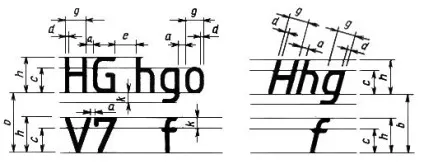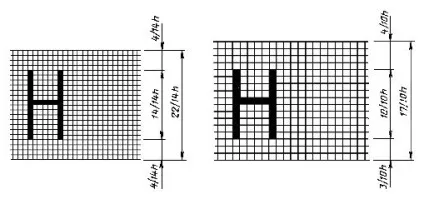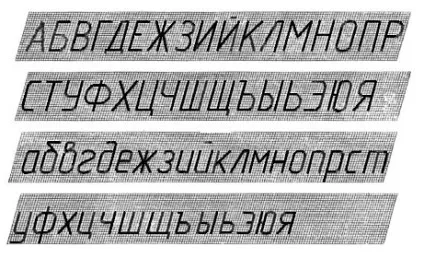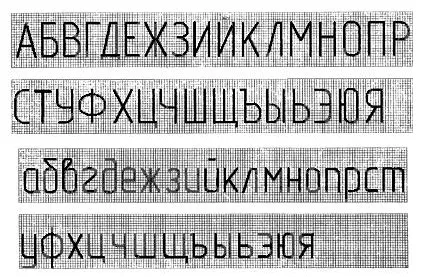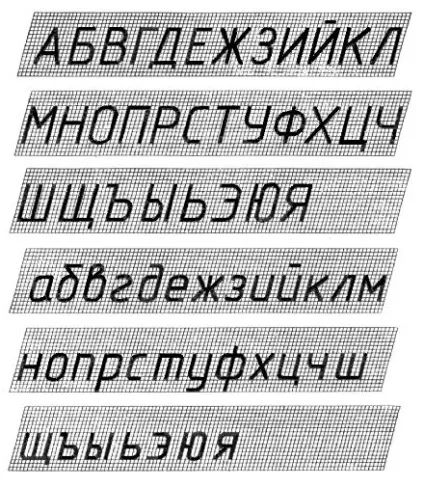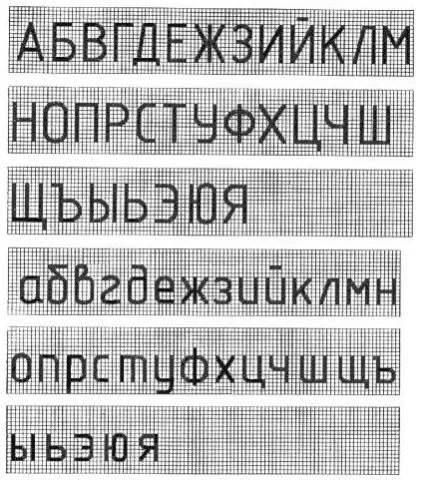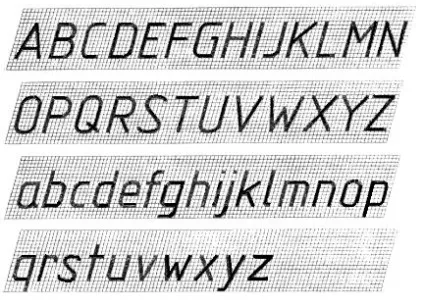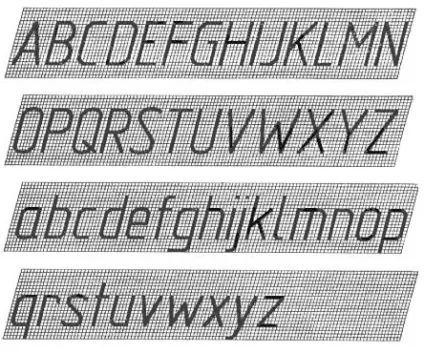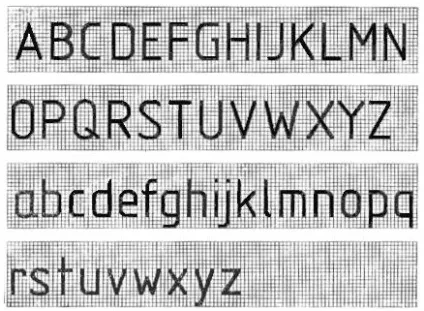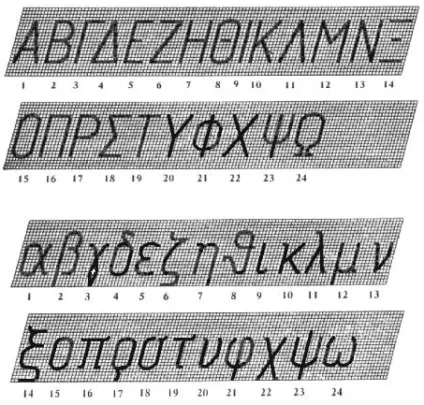
Шрифти креслярські (гост -81 ЕСКД)
1. Терміни та визначення
1.1. Розмір шрифту h - величина, визначена висотою великих літер в міліметрах.
1.2. Висота великих літер h вимірюється перпендикулярно до основи рядка.
Висота малих літер c визначається з відношення їх висоти (без відростків k) до розміру шрифту h. наприклад, c = 7/10 * h (рисунок 1 і 2).
1.3. Ширина буквиg - найбільша ширина літери, виміряна відповідно до рисунок 1 і 2, визначається по відношенню до розміру шрифту h. наприклад, g = 6/10 * h. або по відношенню до товщини лінії шрифту d. наприклад, g = 6 * d
1.4. Товщина лінії шріфтаd - товщина, що визначається в залежності від типу і висоти шрифту.
1.5. Допоміжна сітка - сітка, утворена допоміжними лініями, в які вписуються літери. Крок допоміжних ліній сітки визначається в залежності від товщини ліній шрифту d (черт.3).
2. ТИПИ І РОЗМІРИ ШРИФТУ
2.1. Встановлюються такі типи шрифту:
тип А без нахилу (d = 1/14 * h) з параметрами, наведеними в табл.1;
тип А з нахилом близько 75 ° (d = 1/14 * h) з параметрами, наведеними в табл.1;
тип Б без нахилу (d = 1/10 * h) з параметрами, наведеними в табл.2;
тип Б з нахилом близько 75 ° (d = 1/10 * h) c параметрами, наведеними в табл.2.
1. Відстань α між буквами, сусідні лінії яких не паралельні між собою (наприклад, ГА. АТ), може бути зменшено наполовину, тобто на товщину d лінії шрифту.
2. Мінімальною відстанню між словами e. розділеними знаком пунктуації, є відстань між знаком пунктуації та наступним за ним словом.
При виконанні документів автоматизованим способом допускається застосовувати шрифти, використовувані засобами обчислювальної техніки. У цьому випадку повинні бути забезпечені їх зберігання і передача користувачам документів.
2.2. Встановлюються такі розміри шрифту: (1,8); 2,5; 3,5; 5; 7; 10; 14; 20; 28; 40.
Примітка. Застосування шрифту розміром 1,8 не рекомендується і допускається тільки для типу Б.
2.3. Побудова шрифту в допоміжній сітці показано на черт.4.
2.4. Граничні відхилення розмірів літер і цифр ± 0,5 мм.
3. український АЛФАВИТ (КИРИЛИЦЯ)
3.1. Шрифт типу А з нахилом наведено на черт.5.
3.2. Шрифт типу А без нахилу наведено на черт.6.
3.3. Шрифт типу Б з нахилом наведено на черт.7.
3.4. Шрифт типу Б без нахилу наведено на черт.8.
4. ЛАТИНСЬКИЙ АЛФАВИТ
4.1. Шрифт типу А з нахилом наведено на черт.9.
4.2. Шрифт типу А без нахилу наведено на черт.10.
4.3. Шрифт типу Б з нахилом наведено на черт.11.
4.4. Шрифт типу Б без нахилу наведено на черт.12.
4.5. Види, форма та розташування діакритичних знаків для шрифтів типів А і Б без нахилу наведені в додатку.
Діакритичні знаки для шрифтів з нахилом слід виконувати за тими ж правилами.
5. ГРЕЦЬКИЙ АЛФАВІТ
5.1. Шрифт типу А з нахилом наведено на черт.13.
5.2. Шрифт типу А без нахилу наведено на черт.14.
5.3. Шрифт типу Б з нахилом наведено на черт.15.
5.4. Шрифт типу Б без нахилу наведено на черт.16.
5.5. Найменування букв грецького алфавіту, наведених на черт.13-16: